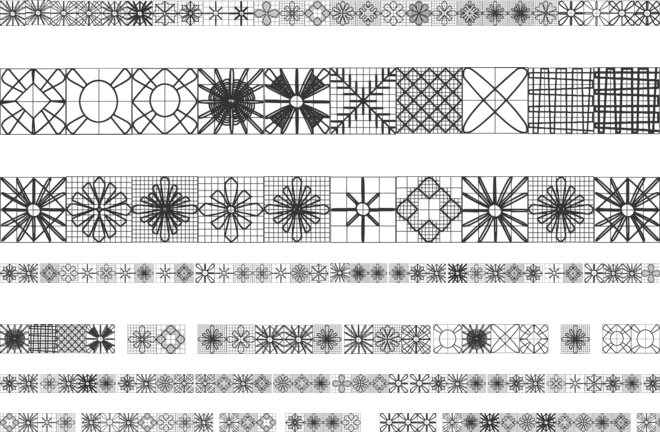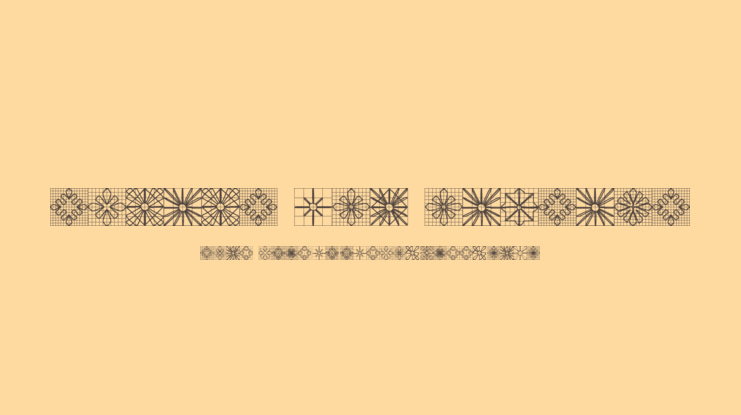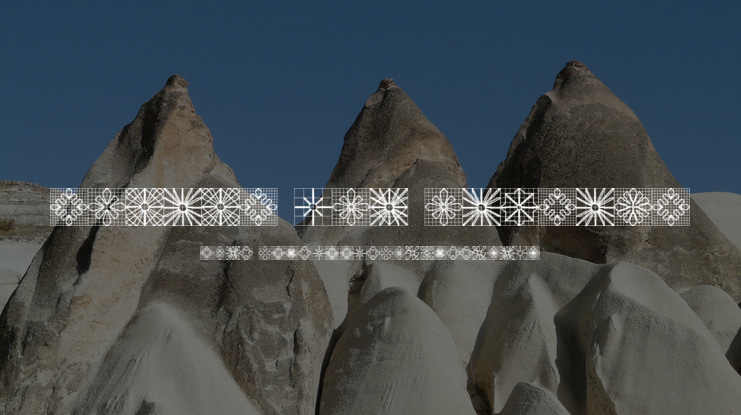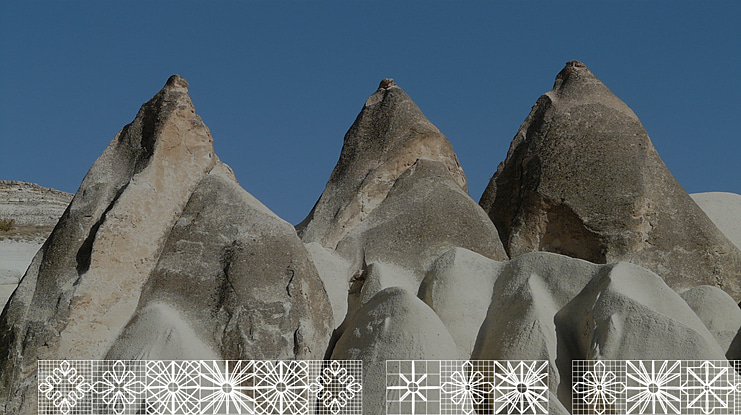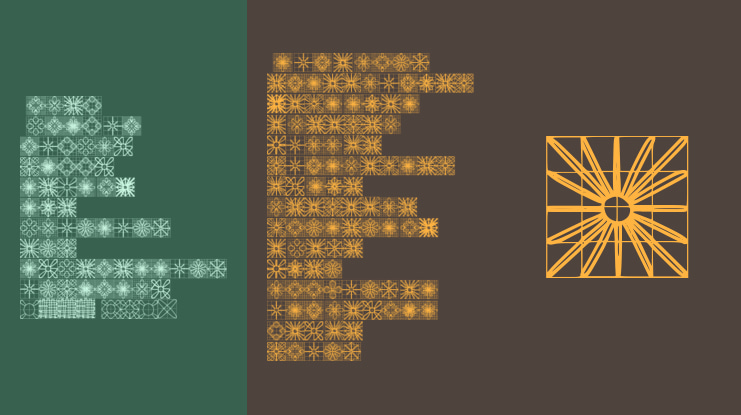
Bordado File Alagoano Font Family
O projeto dingbat bordado filé nas versões 1 e 2, foram desenvolvido pela autora Géssy Ferreira, com inspiração nos registros
dos pontos desse bordado Alagoano do Pontal da Barra, de forma a tentar fortalecer e divulgar ainda mais seus pontos em outros meios, além do que
estamos acostumados (roupas e acessorios), mas também pela internet mostrando aspectos da cultura local.